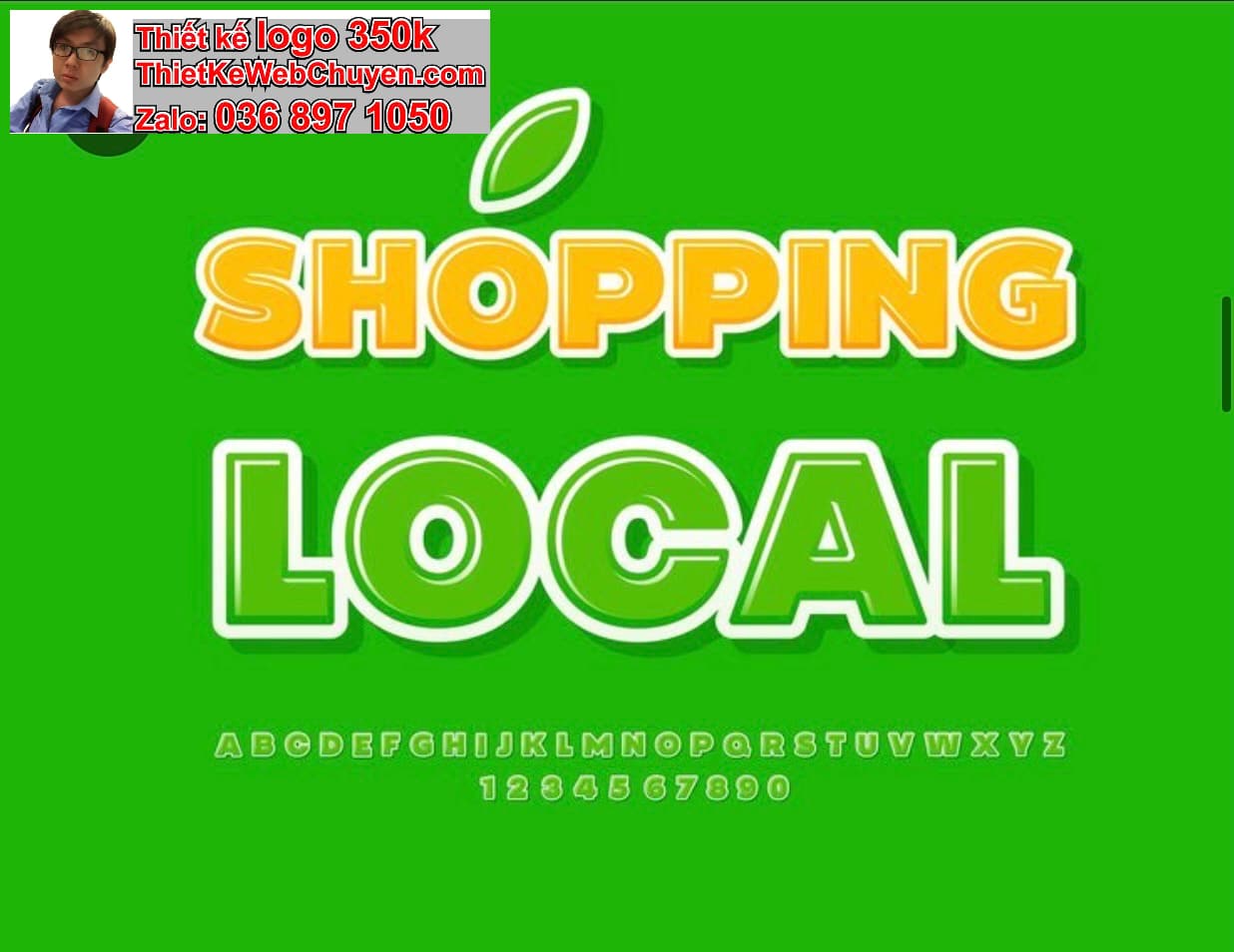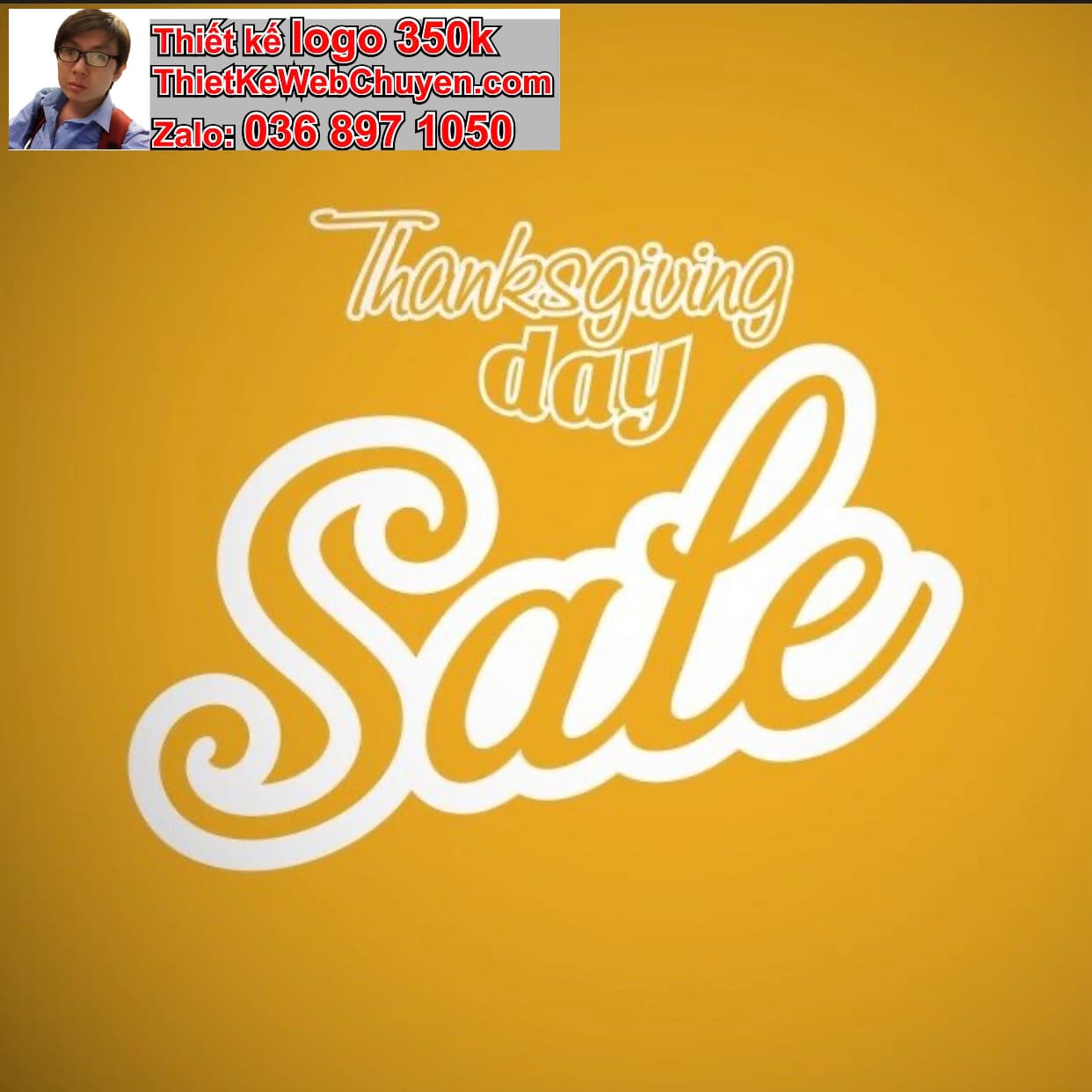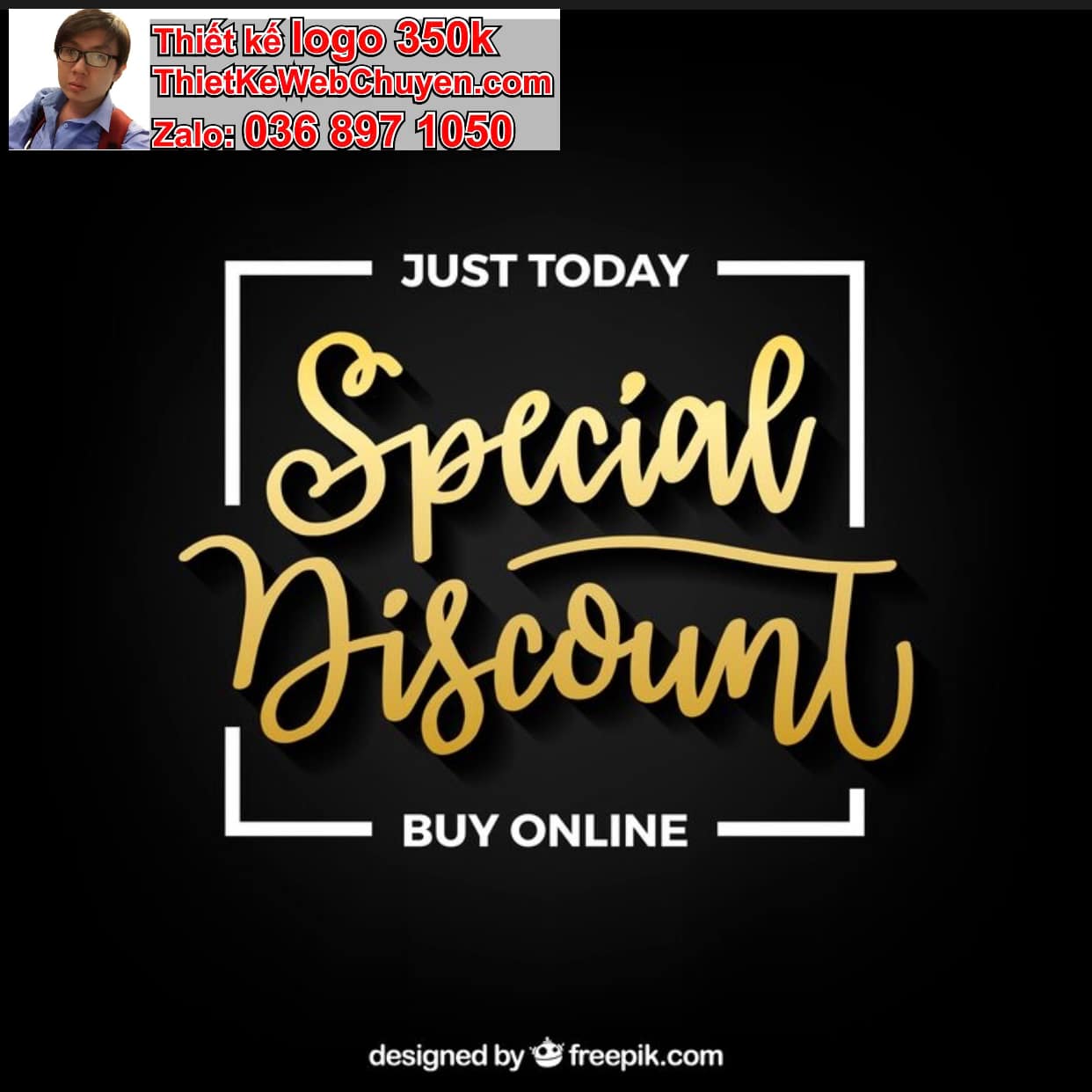
Để tìm được font chữ đẹp cho logo công ty giá rẻ mà vẫn đảm bảo tính chuyên nghiệp và thu hút, bạn cần hiểu rõ bản sắc thương hiệu, khám phá các kho font miễn phí chất lượng cao và áp dụng nguyên tắc phối hợp hợp lý. Việc lựa chọn khôn ngoan sẽ giúp logo của bạn nổi bật, dễ ghi nhớ và truyền tải thông điệp hiệu quả mà không tốn kém chi phí bản quyền.
Tại sao việc chọn font chữ đẹp cho logo công ty giá rẻ lại quan trọng?
Việc lựa chọn font chữ đẹp cho logo công ty giá rẻ không chỉ đơn thuần là vấn đề thẩm mỹ mà còn là một yếu tố chiến lược quan trọng trong việc xây dựng thương hiệu. Logo là bộ mặt của doanh nghiệp, và font chữ chính là “giọng điệu” truyền tải thông điệp đó. Một font chữ phù hợp có thể tạo ra sự khác biệt lớn, giúp logo của bạn nổi bật trong thị trường cạnh tranh.
Tâm lý học của font chữ và ảnh hưởng đến thương hiệu
Mỗi kiểu font chữ đều mang trong mình một tâm lý và cảm xúc riêng biệt. Ví dụ, font serif thường gợi cảm giác truyền thống, đáng tin cậy và sang trọng, rất phù hợp với các ngành nghề như luật, tài chính hay thời trang cao cấp. Ngược lại, font sans-serif lại mang đến sự hiện đại, tối giản, rõ ràng và thân thiện, lý tưởng cho các công ty công nghệ, khởi nghiệp hoặc thương hiệu muốn thể hiện sự đổi mới. Việc hiểu rõ tâm lý học này sẽ giúp bạn chọn được font chữ đẹp cho logo công ty giá rẻ phù hợp nhất với giá trị cốt lõi của thương hiệu.
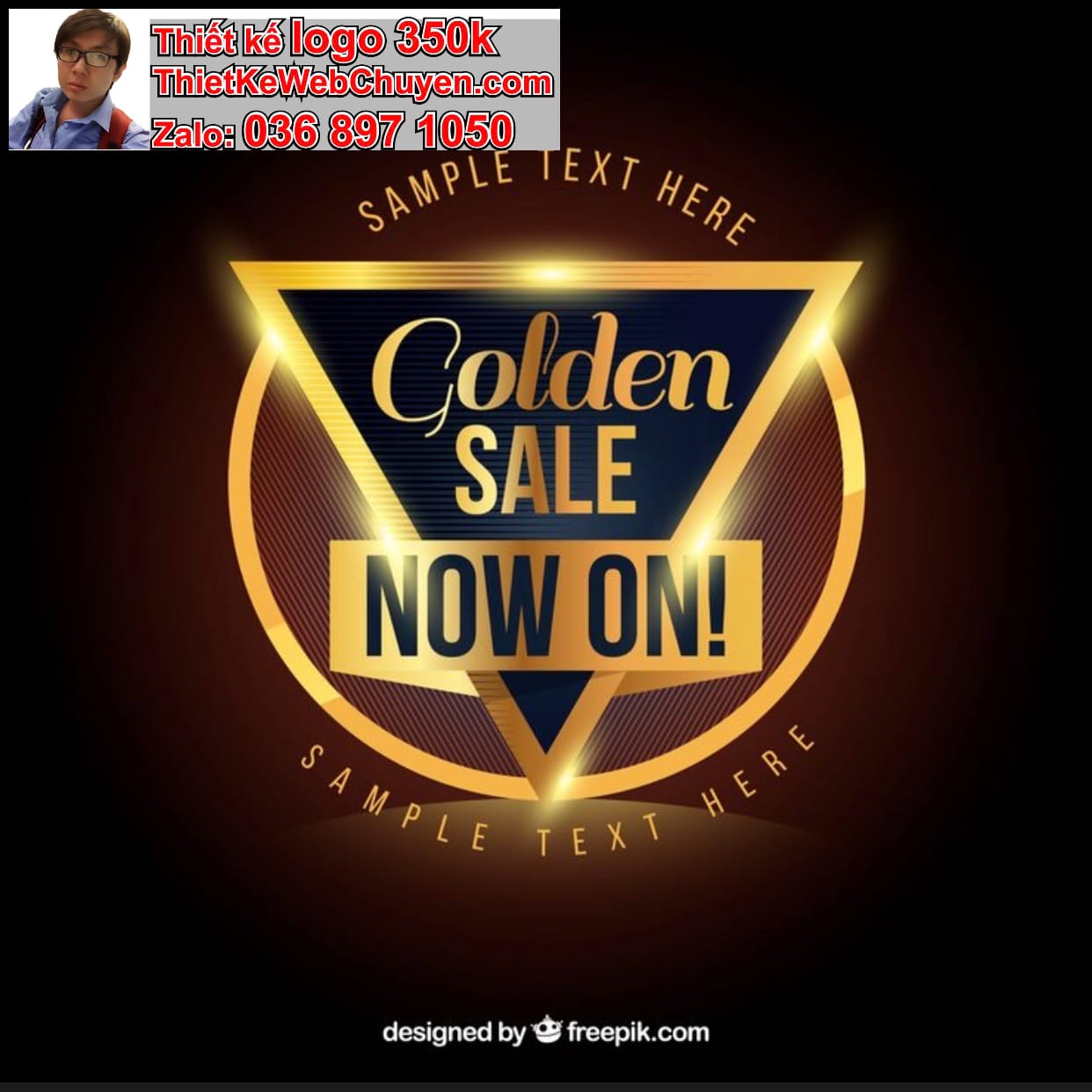
Phản ánh cá tính thương hiệu qua font chữ đẹp cho logo công ty giá rẻ
Logo không chỉ là hình ảnh, nó còn là câu chuyện về thương hiệu của bạn. Font chữ đẹp cho logo công ty giá rẻ chính là một phần của câu chuyện đó. Nó có thể nói lên sự năng động, sáng tạo, uy tín hay sự ấm áp của công ty bạn. Một font chữ độc đáo, được lựa chọn kỹ lưỡng sẽ giúp khách hàng cảm nhận được cá tính riêng biệt mà không cần phải đọc bất kỳ mô tả nào. Điều này đặc biệt quan trọng khi bạn muốn tạo ra một logo công ty giá rẻ nhưng vẫn chuyên nghiệp và có sức hút.
Dễ nhận diện và ghi nhớ: Giá trị cốt lõi của font chữ đẹp cho logo công ty giá rẻ
Trong một thế giới tràn ngập thông tin, việc để lại ấn tượng sâu sắc là chìa khóa. Một font chữ đẹp cho logo công ty giá rẻ có khả năng dễ đọc và dễ nhớ sẽ giúp khách hàng nhận diện thương hiệu của bạn ngay lập tức, dù là trên biển quảng cáo lớn hay biểu tượng ứng dụng nhỏ. Điều này không chỉ tăng cường sự nhận diện mà còn xây dựng lòng tin và sự trung thành từ phía khách hàng. Mục tiêu là tạo ra một font chữ đẹp cho logo công ty giá rẻ mà vẫn in sâu vào tâm trí người xem.
Làm thế nào để chọn font chữ đẹp cho logo công ty giá rẻ nhưng vẫn chuyên nghiệp?
Việc chọn một font chữ đẹp cho logo công ty giá rẻ mà vẫn giữ được tính chuyên nghiệp và hiệu quả là hoàn toàn khả thi nếu bạn tuân thủ các bước và nguyên tắc nhất định. Dưới đây là lộ trình chi tiết giúp bạn đưa ra quyết định sáng suốt.
Bước 1: Hiểu rõ thương hiệu và đối tượng khách hàng của bạn
Trước khi bắt tay vào tìm kiếm font chữ đẹp cho logo công ty giá rẻ, hãy tự đặt ra những câu hỏi cốt lõi:
- Giá trị cốt lõi của công ty bạn là gì? (Ví dụ: Đổi mới, truyền thống, thân thiện, sang trọng, bền vững…)
- Bạn muốn khách hàng cảm nhận điều gì khi nhìn thấy logo của bạn?
- Đối tượng khách hàng mục tiêu của bạn là ai? (Độ tuổi, giới tính, sở thích, thu nhập…)
- Ngành nghề của bạn có đặc thù gì về mặt thẩm mỹ không?
Trả lời những câu hỏi này sẽ giúp bạn thu hẹp phạm vi lựa chọn và định hướng phong cách cho font chữ đẹp cho logo công ty giá rẻ.
Bước 2: Phân loại các kiểu font chữ phổ biến và ứng dụng của chúng
Hiểu các loại font chữ cơ bản sẽ giúp bạn nhanh chóng xác định được phong cách phù hợp cho font chữ đẹp cho logo công ty giá rẻ của mình.
- Font Serif:
- Đặc điểm: Có các nét gạch nhỏ (serif) ở cuối mỗi ký tự.
- Cảm nhận: Truyền thống, uy tín, đáng tin cậy, cổ điển, trang trọng, sang trọng.
- Phù hợp với: Ngành tài chính, luật, giáo dục, thời trang cao cấp, báo chí, xuất bản.
- Ví dụ: Times New Roman, Georgia, Playfair Display.
- Font Sans-serif:
- Đặc điểm: Không có nét gạch nhỏ ở cuối ký tự (“sans” nghĩa là “không” trong tiếng Pháp).
- Cảm nhận: Hiện đại, tối giản, rõ ràng, thân thiện, sạch sẽ, năng động.
- Phù hợp với: Công nghệ, khởi nghiệp, website, ứng dụng di động, thương hiệu muốn sự đổi mới, dễ tiếp cận.
- Ví dụ: Arial, Helvetica, Open Sans, Montserrat.
- Font Script:
- Đặc điểm: Mô phỏng chữ viết tay, thường có các nét nối liền mạch hoặc trông rất nghệ thuật.
- Cảm nhận: Thanh lịch, cá nhân, sáng tạo, sang trọng, nữ tính, lãng mạn.
- Phù hợp với: Sản phẩm thủ công, tiệm bánh, nhà hàng, sự kiện, thời trang, nhiếp ảnh.
- Lưu ý: Cần cẩn trọng để đảm bảo khả năng đọc, đặc biệt ở kích thước nhỏ.
- Font Display/Decorative:
- Đặc điểm: Rất độc đáo, thường được thiết kế để gây ấn tượng mạnh, có tính trang trí cao.
- Cảm nhận: Độc đáo, cá tính, vui nhộn, mạnh mẽ, thu hút sự chú ý.
- Phù hợp với: Tiêu đề, quảng cáo, thương hiệu muốn tạo dấu ấn riêng biệt.
- Lưu ý: Nên sử dụng tiết chế, không dùng cho các khối văn bản dài.